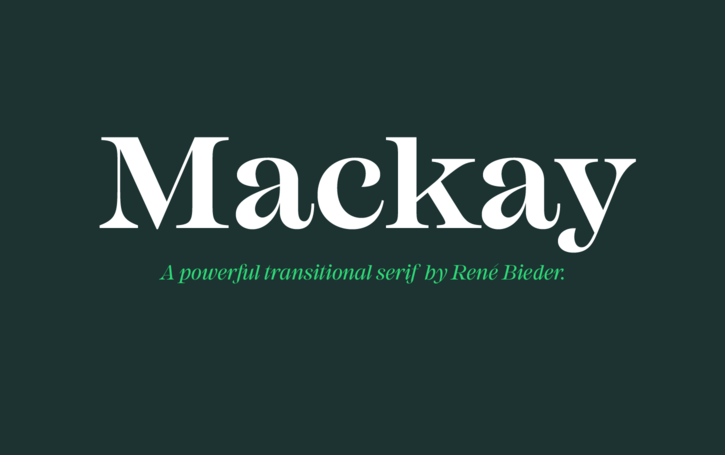
Mackay Font Family – Download Grátis
Através da nova família Mackay, introduzimos uma fonte poderosa que combina seis pesos para atender às necessidades do design no ambiente digital e impressão. A Mackay foi projetada por Rene Bieder inspirada nos estilos serif tradicionais dos séculos anteriores. Uma das características mais notáveis da Mackay é o uso de serifs curiosos nas letras maiúsculas, especialmente em E, F, L e T. Essa originalidade se baseia no “Ronaldson”, um design de Alexander Kay datado de 1884, uma fonte que tem influência sobre a família Mackay. As letras minúsculas seguem o modelo antigo da Antiqua com traços marcando influências do início do século XX. O uso único e intrigante dos serifs na letra maiúscula e sua infusão de estilo tradicional em letras minúsculas fazem desta fonte Mackay uma escolha inteligente para designers que valorizam a transição entre os estilos serif tradicionais e modernos. Engane-se se pensar que Mackay é apenas mais um recurso na sua gama, é uma fonte poderosa com uma personalidade única que vale a pena explorar.